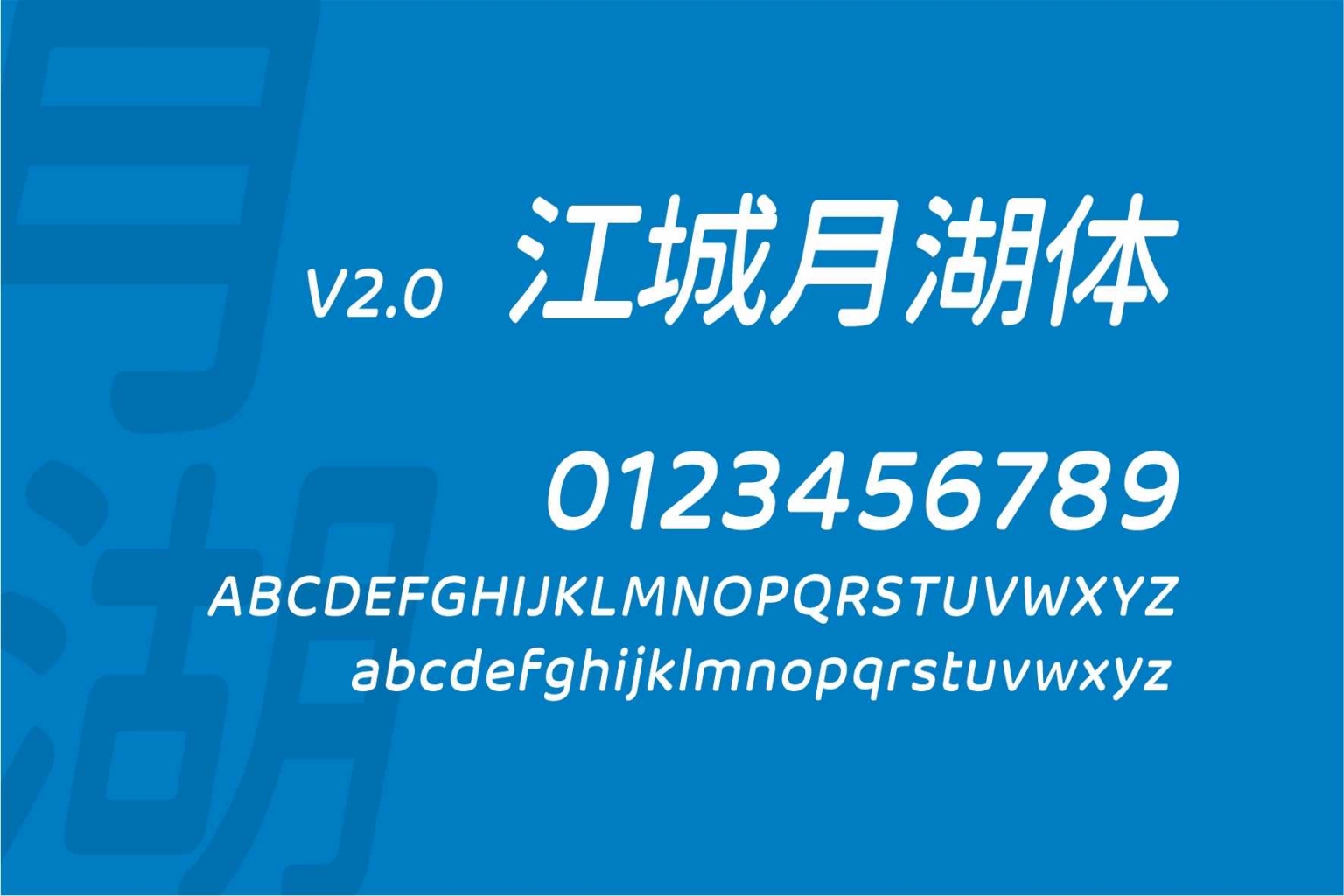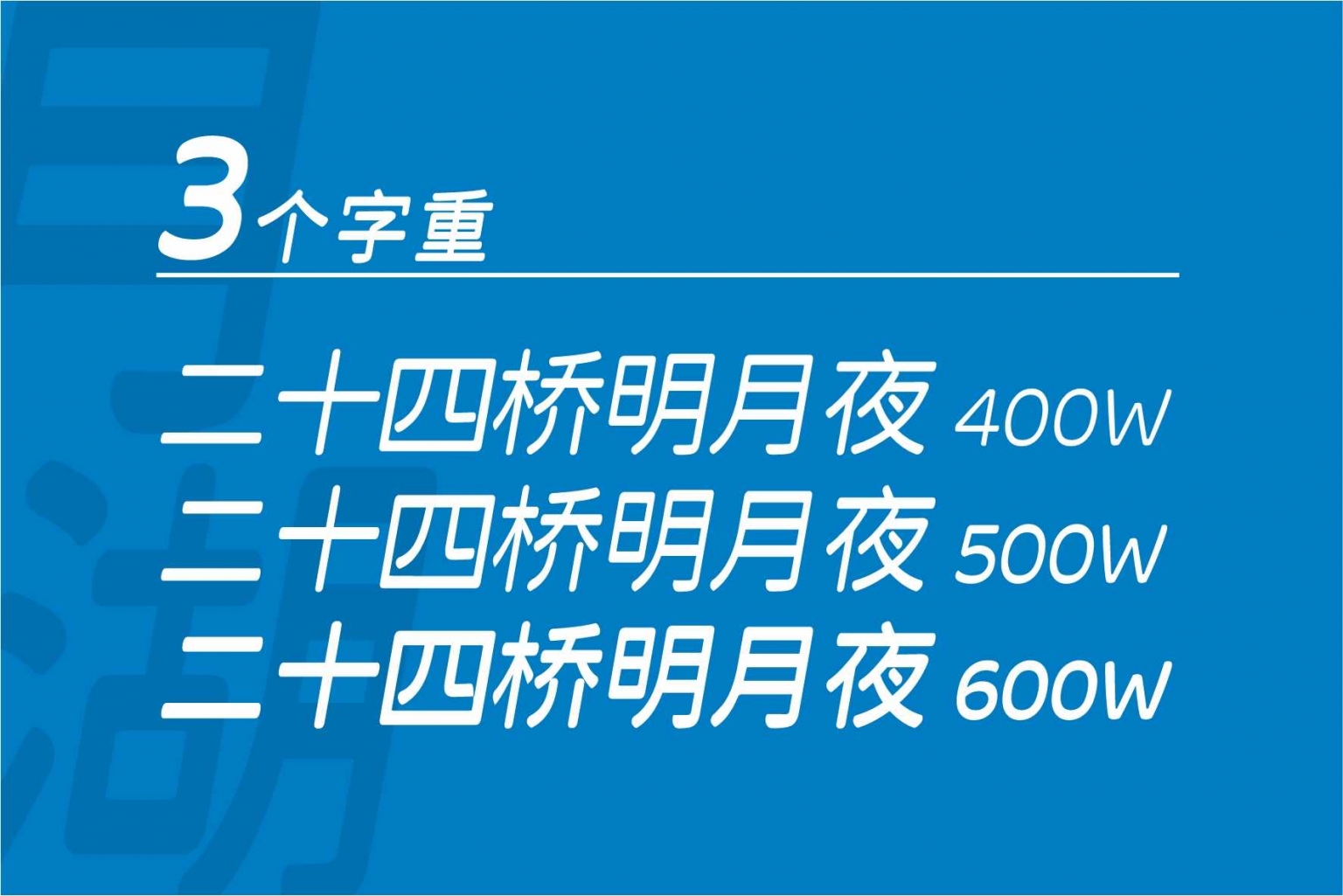
江城月湖体是由设计师刘鹏(微博 @设裂星辰)创作的一款免费可商用的斜体圆体字体,基于同样是“江城” 字体家族系列中的江城圆体改造而成。
笔画处理上,江城月湖体与江城知音体的刚好相反,知音体是横向减细、纵向增粗,而月湖体则是横向增粗,纵向减细。而且整体字形统一向右倾斜 10 度,既有强烈的视觉效果,也赋予文字动感与活力。
江城月湖体提供 3 种(400W、500W、600W)字重,字符集覆盖简体和繁体中文,并支持基本的拉丁文、日文、韩文等,可以满足不同设计需求。
江城月湖体 vs 江城知音体:
| 对比项 | 江城月湖体 | 江城知音体 |
|---|
| 字体结构 | 斜体(右倾 10°) | 无明显倾斜设计 |
| 笔画特征 | 横粗竖细 | 横细竖粗 |
| 视觉气质 | 柔美、轻盈、舒展、文艺 | 稳重、力量、醒目、现代 |
| 字重数量 | 3 字重(400/500/600W) | 3 字重(400/500/600W) |
| 字符数量 | 约 6763 简繁汉字 + 英文数字 | 约 6763 简繁汉字 + 英文数字 |
| 整体感觉 | 偏优雅、柔和、女性化 | 偏硬朗、大气、商务感 |
| 适用场景 | 文艺海报、文创、清新标题、女性品牌 | 电商大标题、活动海报、品牌 LOGO、强视觉标题 |
| 基础原型 | 江城圆体改造 | 江城圆体改造 |